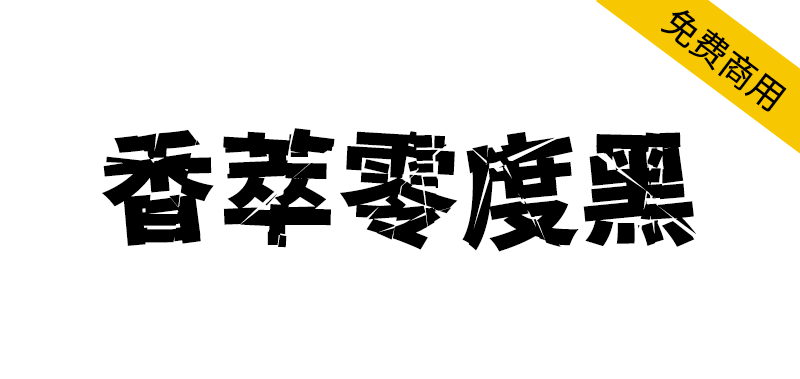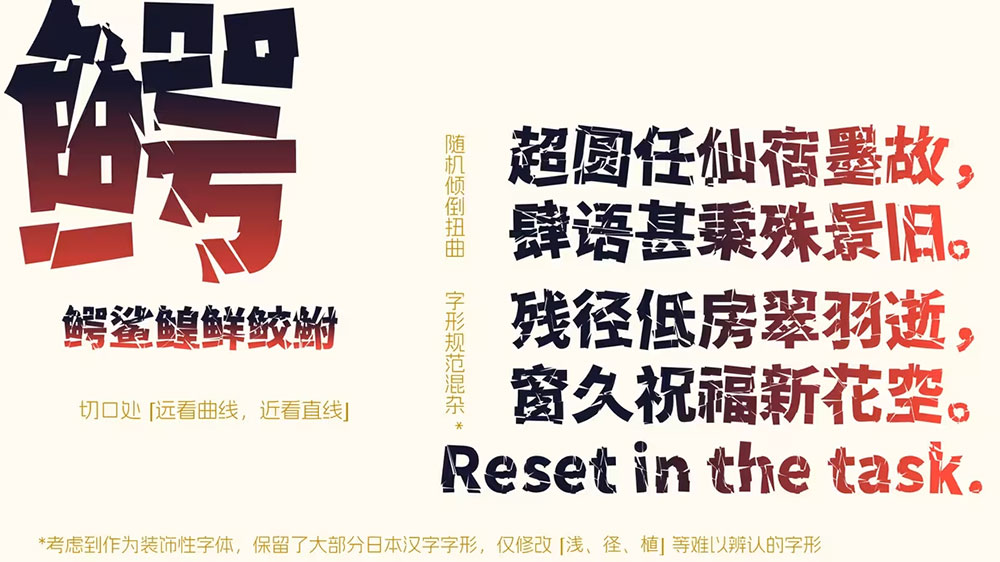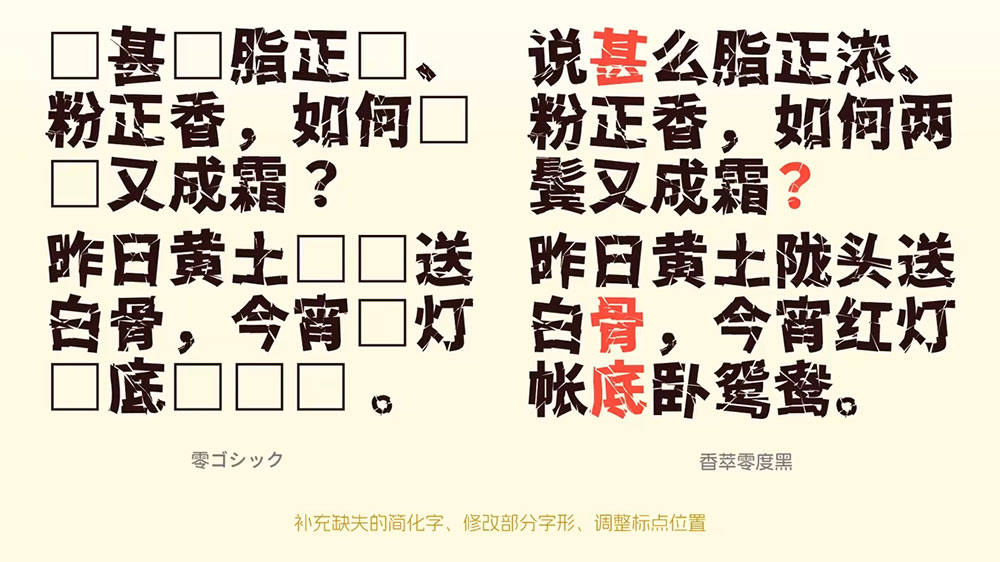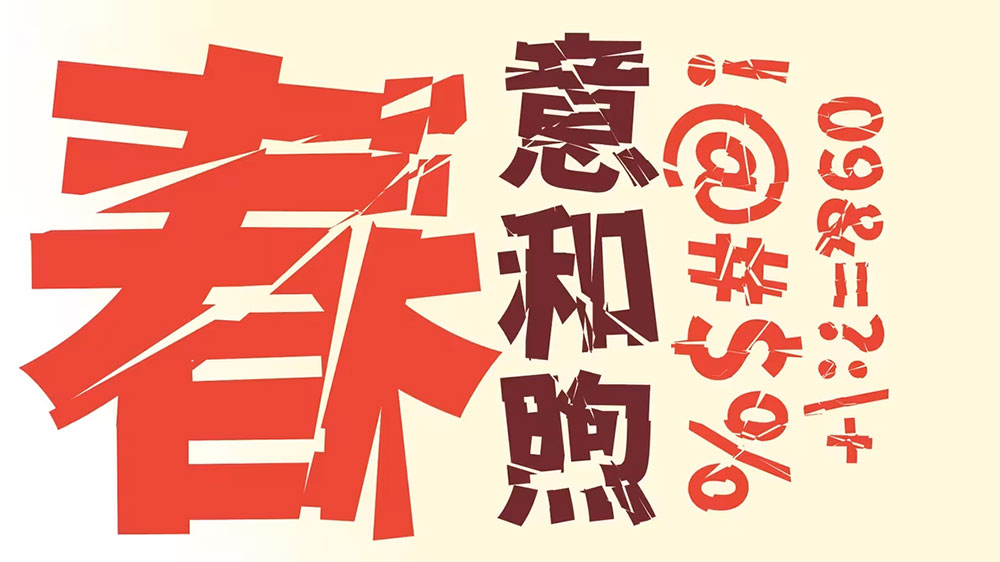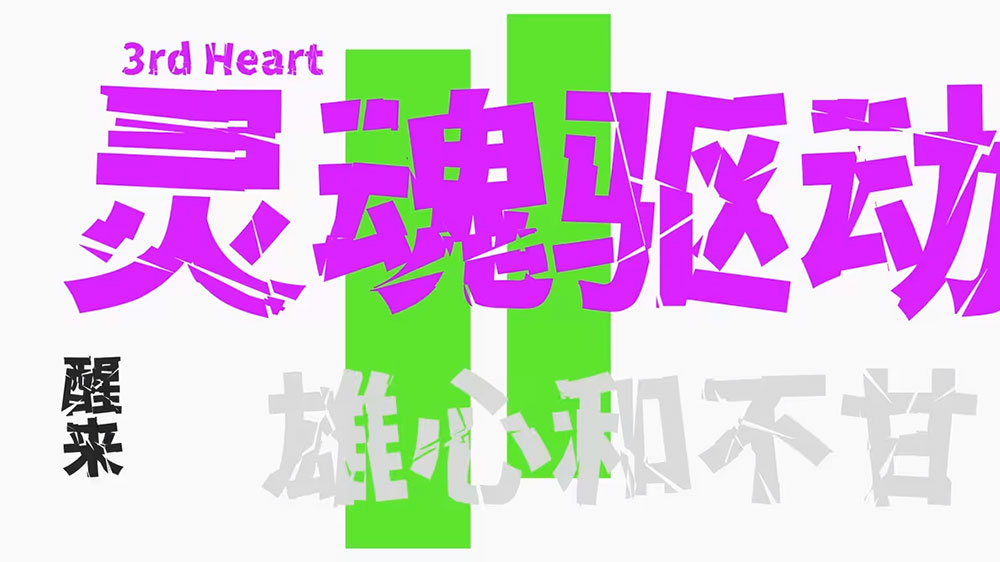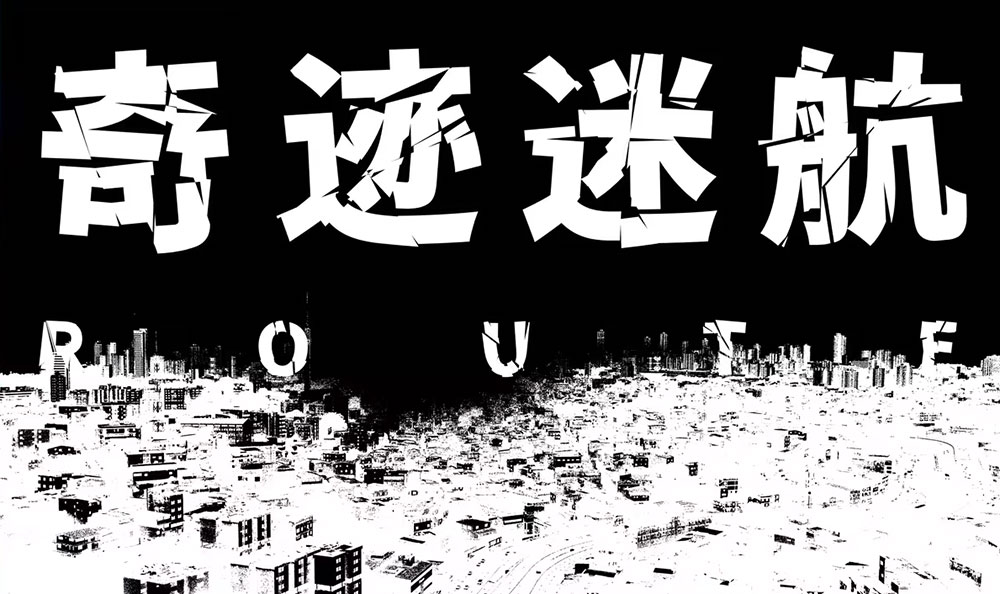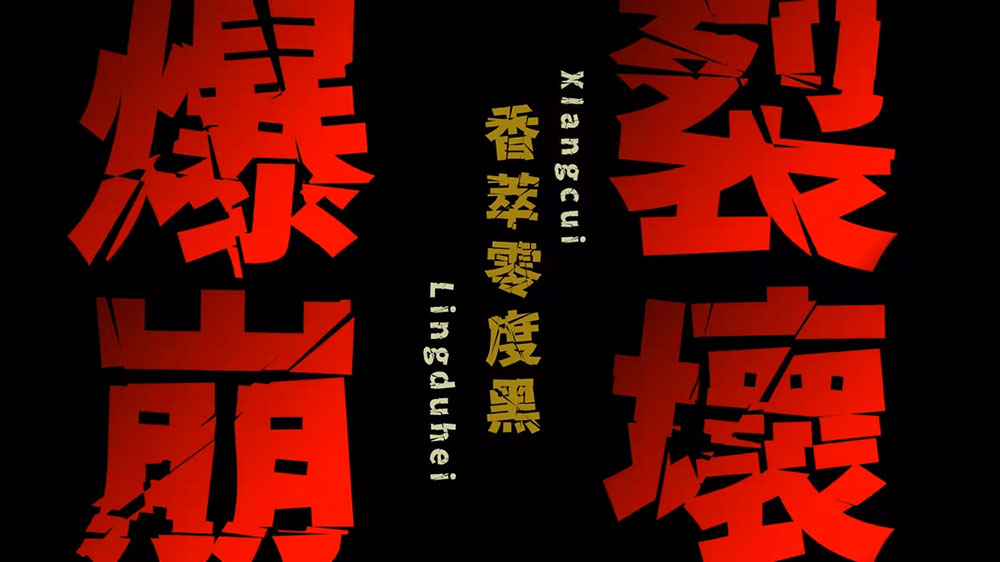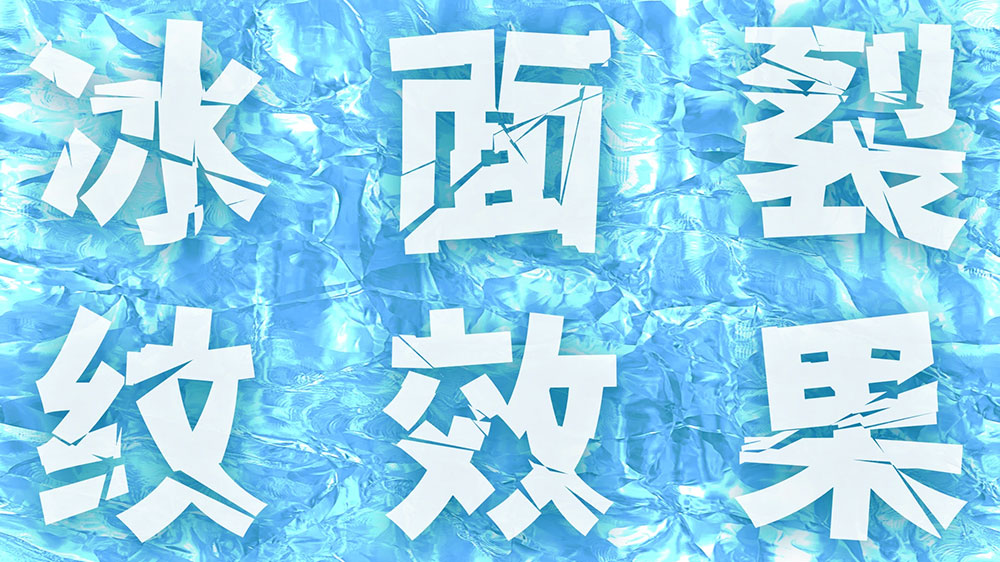
香萃零度黑是日文字体 “ 零ゴシック ” 的简化字补齐版本,字体的冲击性很强,具有非常独特的个性,切割与扭曲明显。本字体属于开源项目,允许全社会免费使用。
在字体的笔画上做了扭曲、分裂的设计,在切口处呈现远看曲线、近看直线的效果。考虑到作为装饰性字体,(在不影响辨识的情况下)部分日本汉字字形仍然保留。根据简体中文书写习惯,微调了标点的位置。目前有近7000简化字。
破碎的字体像冰面纹理,源字体名“零ゴシック”,ゴシック即gothic,意为黑体字,香萃零度黑由此得名。